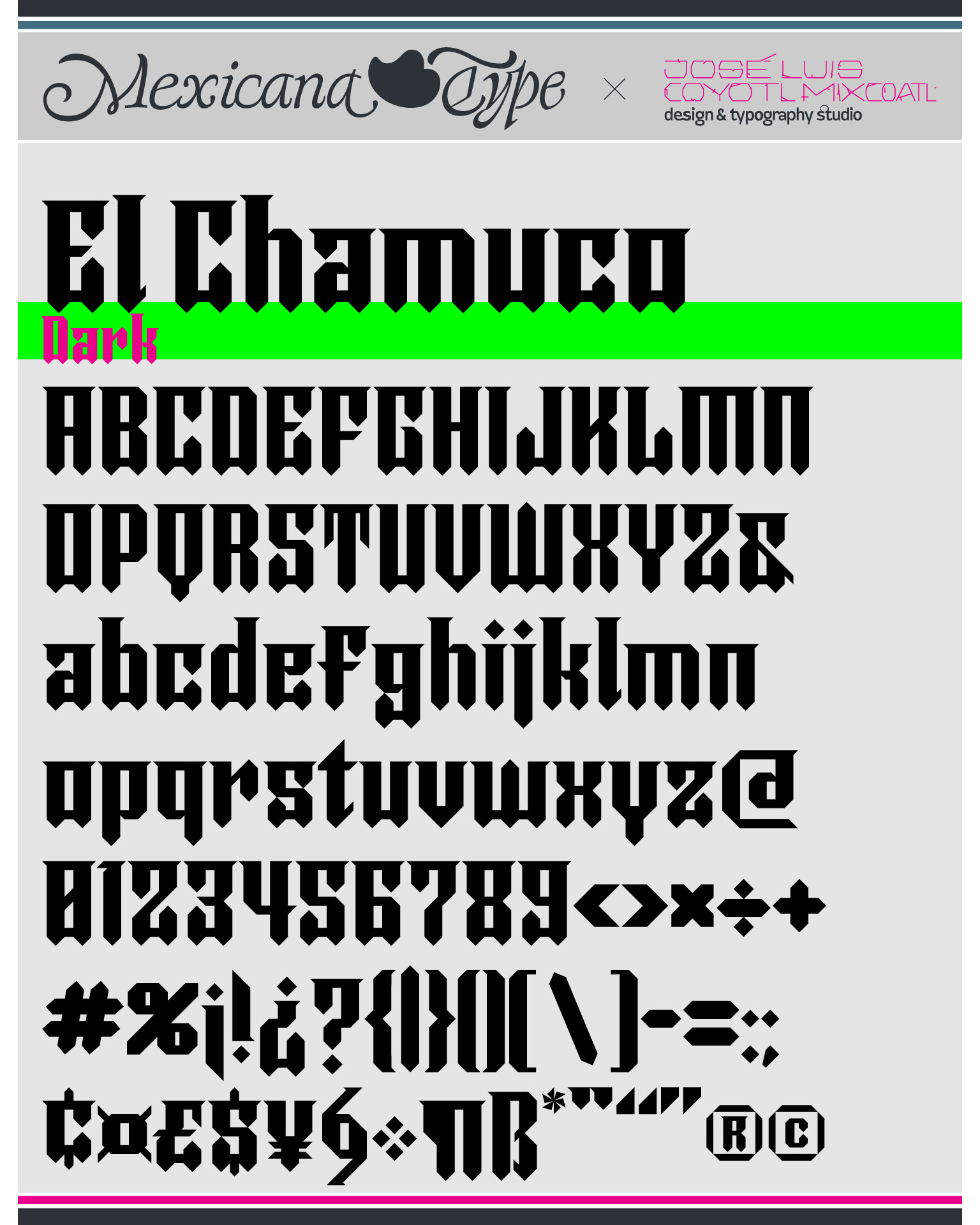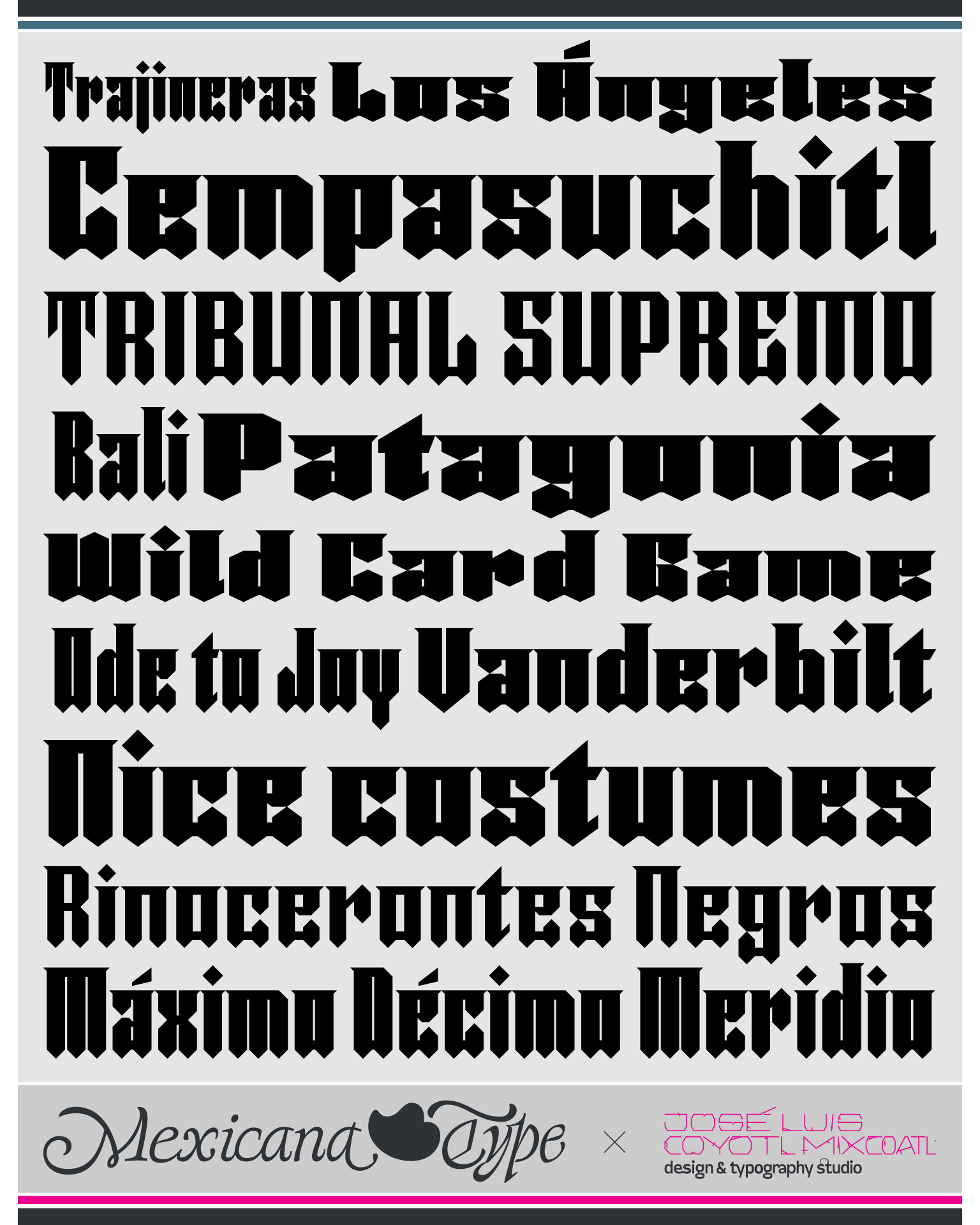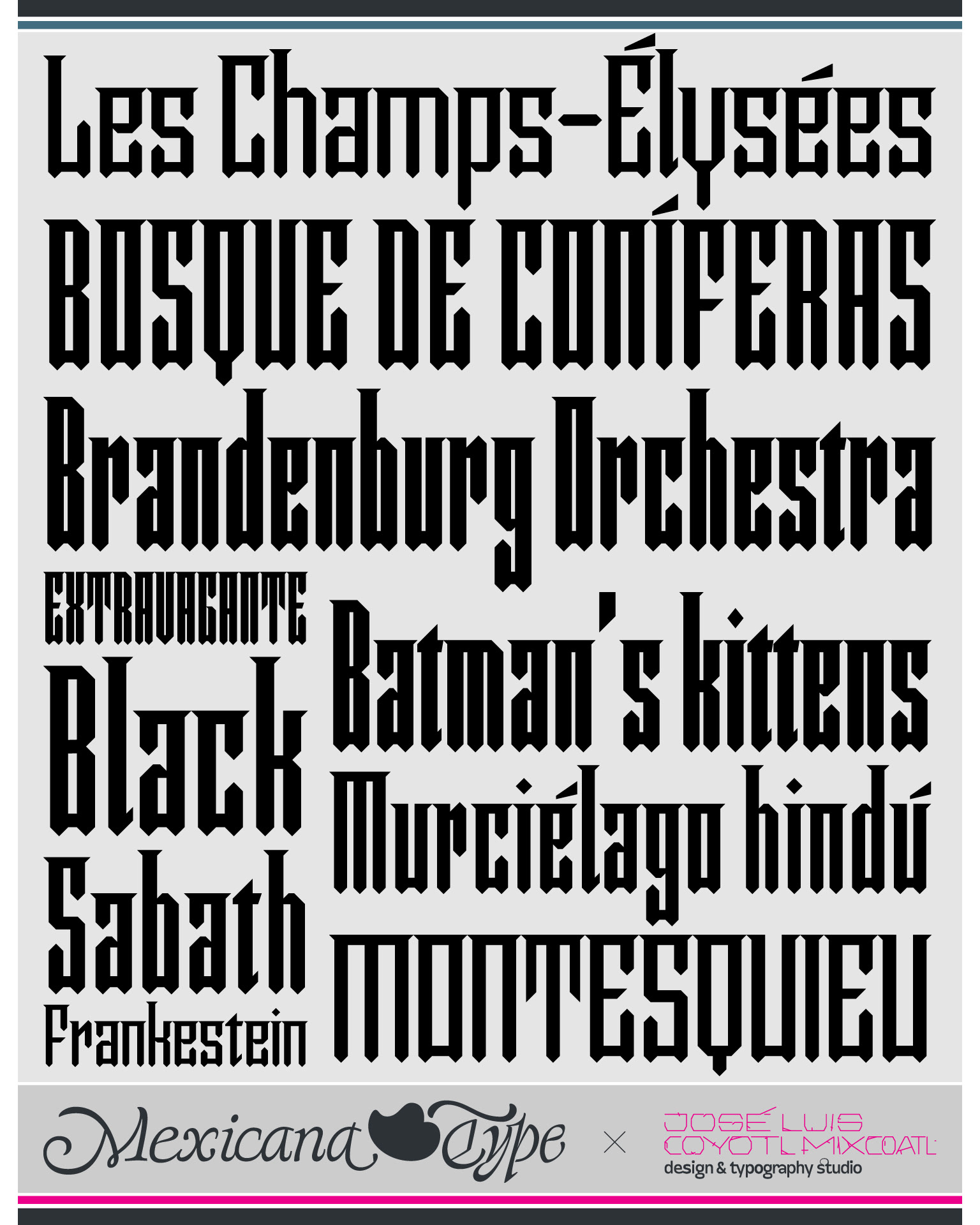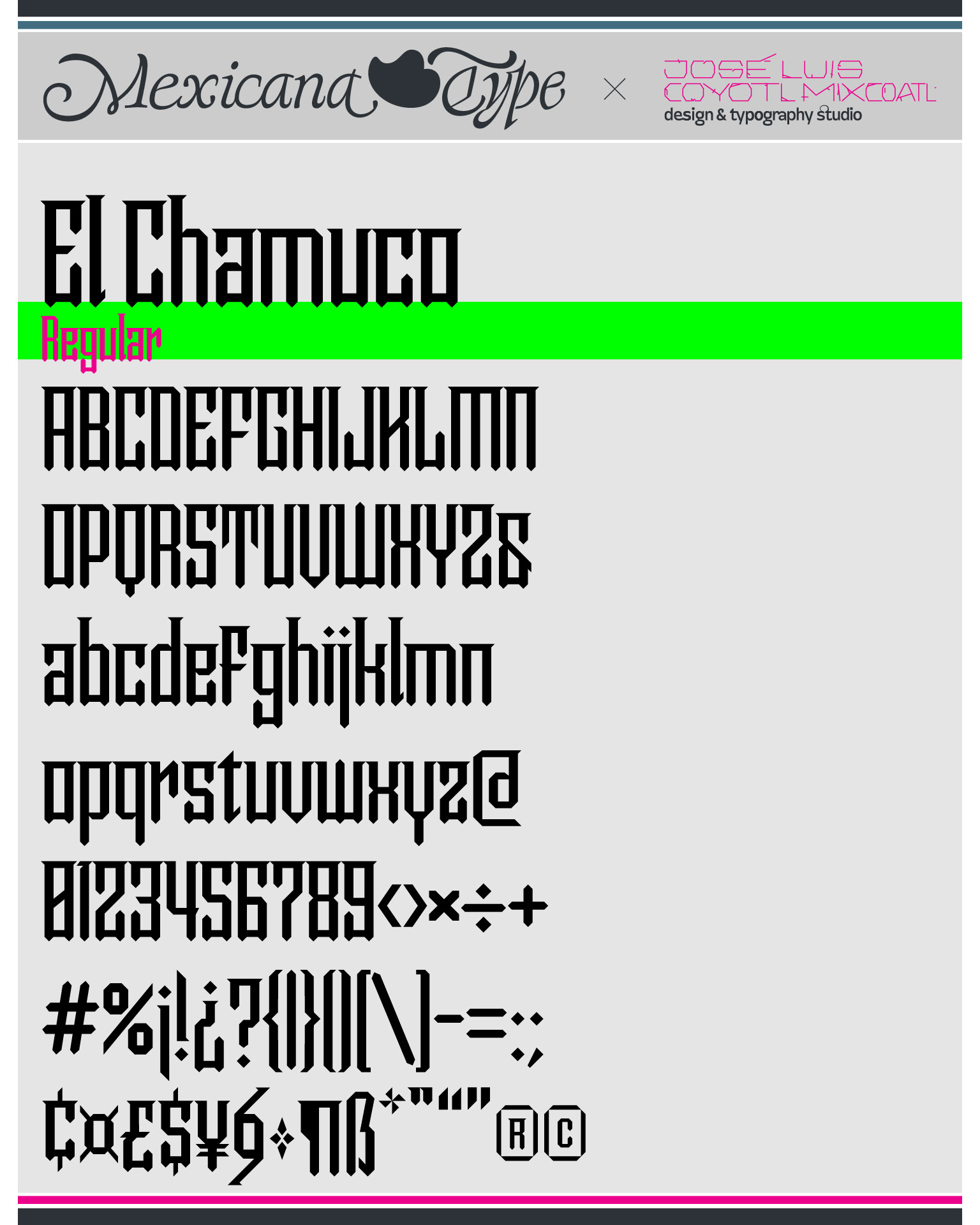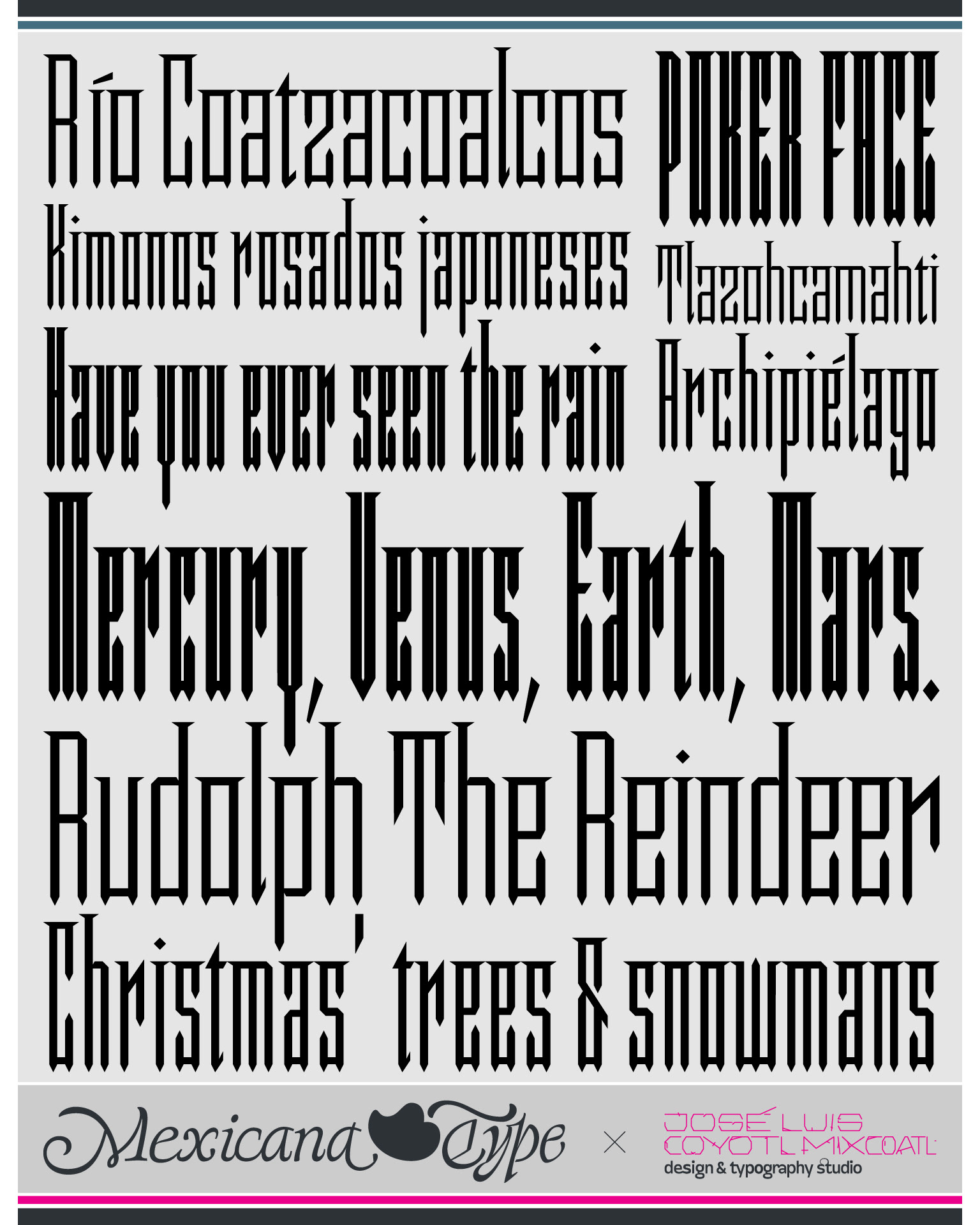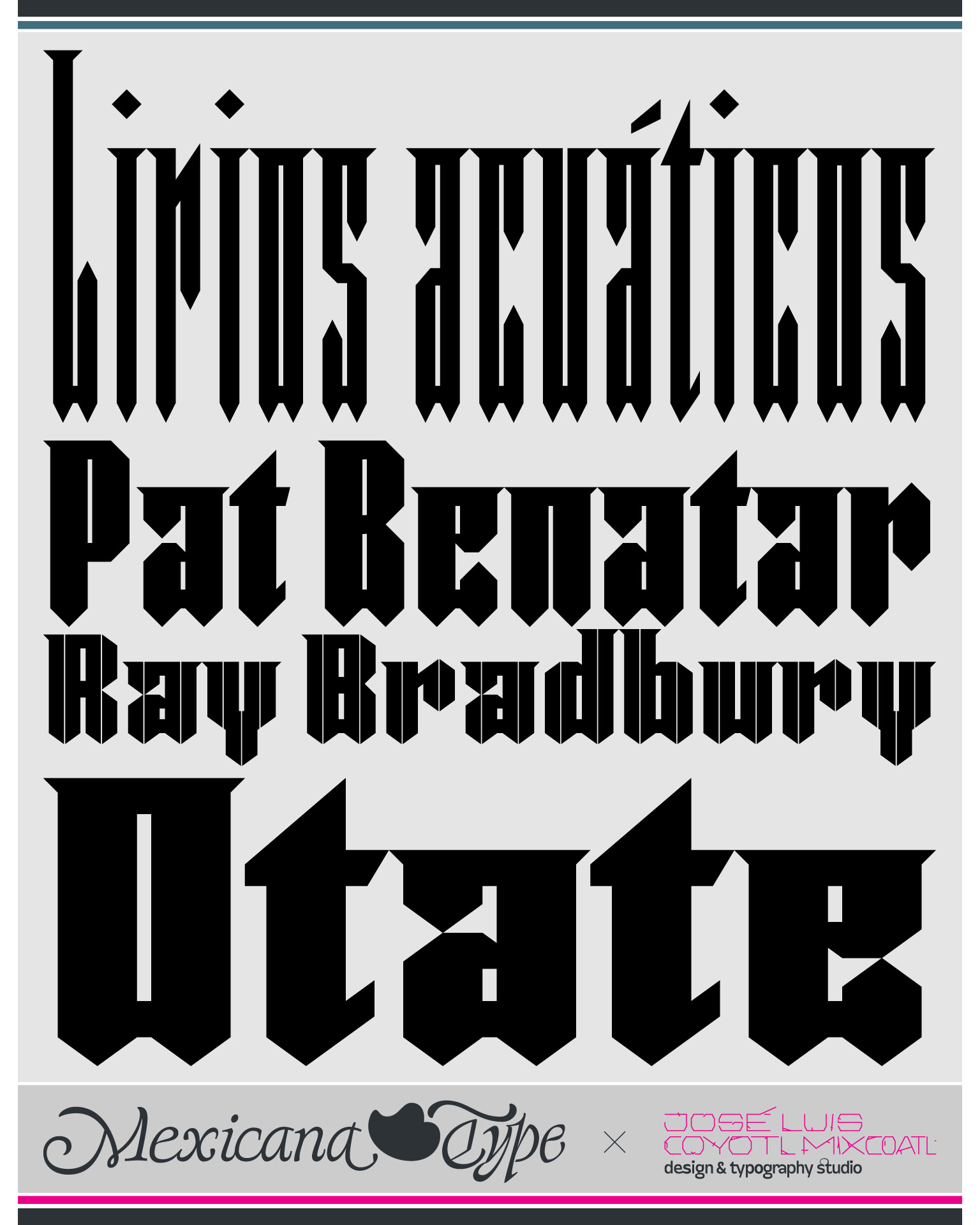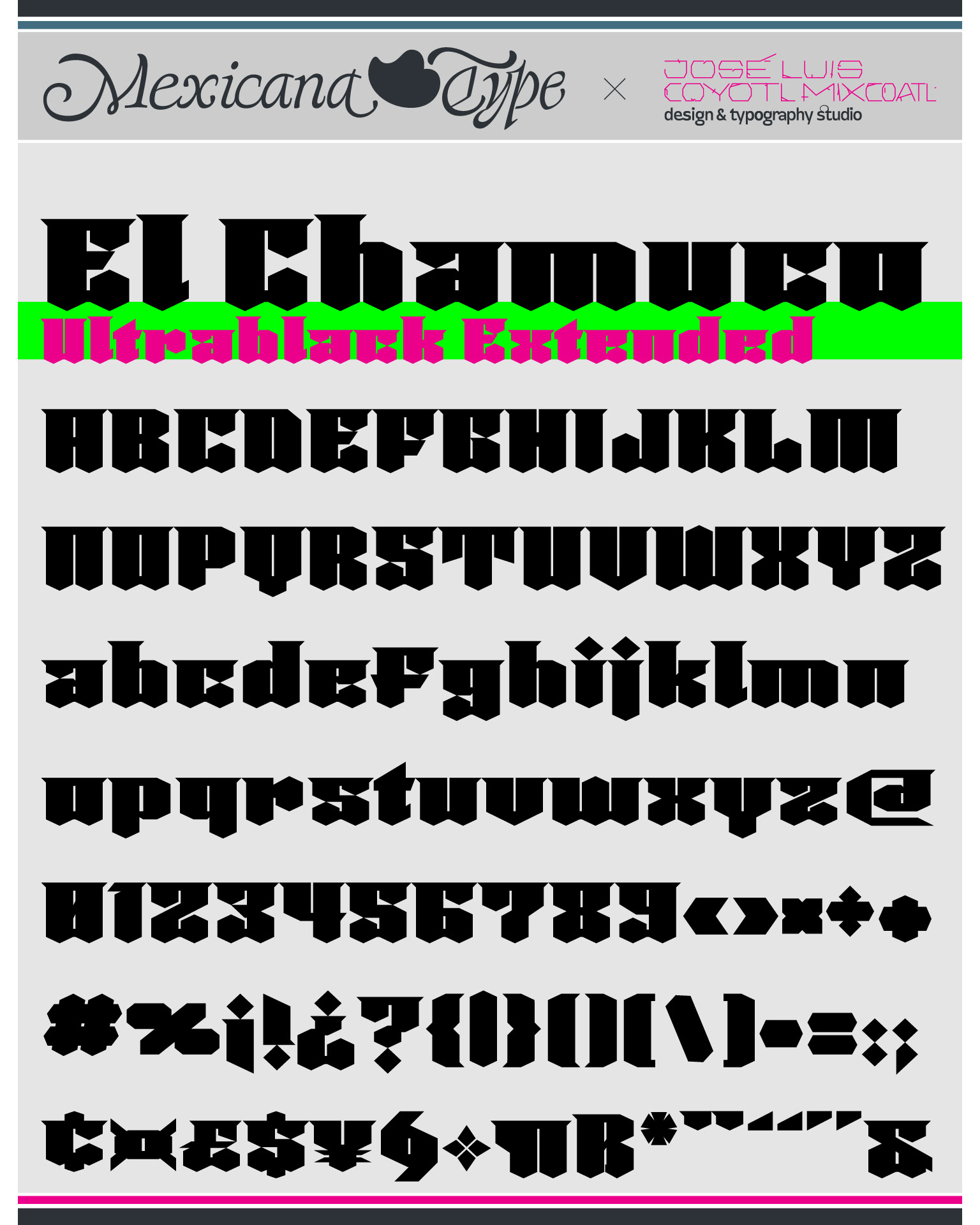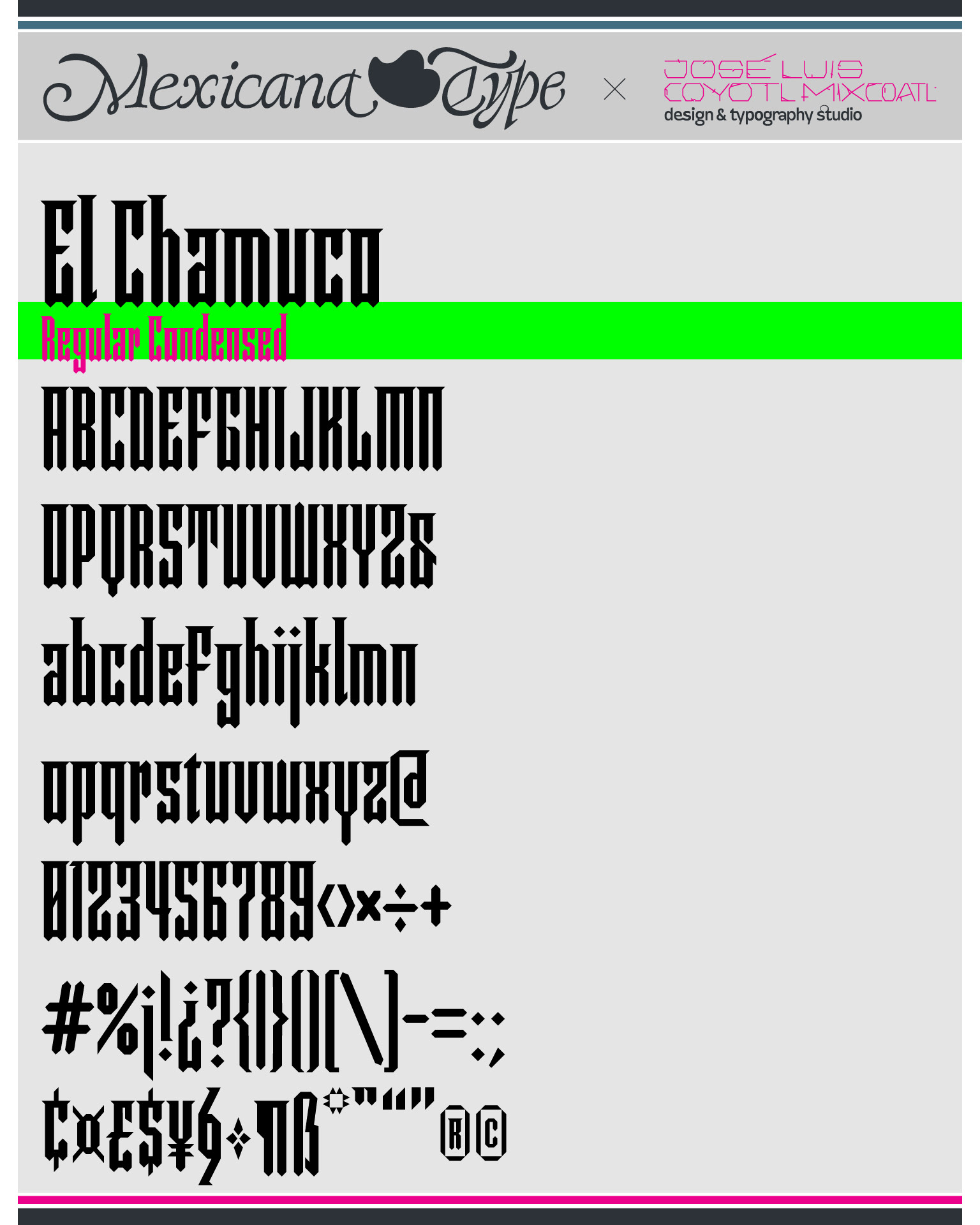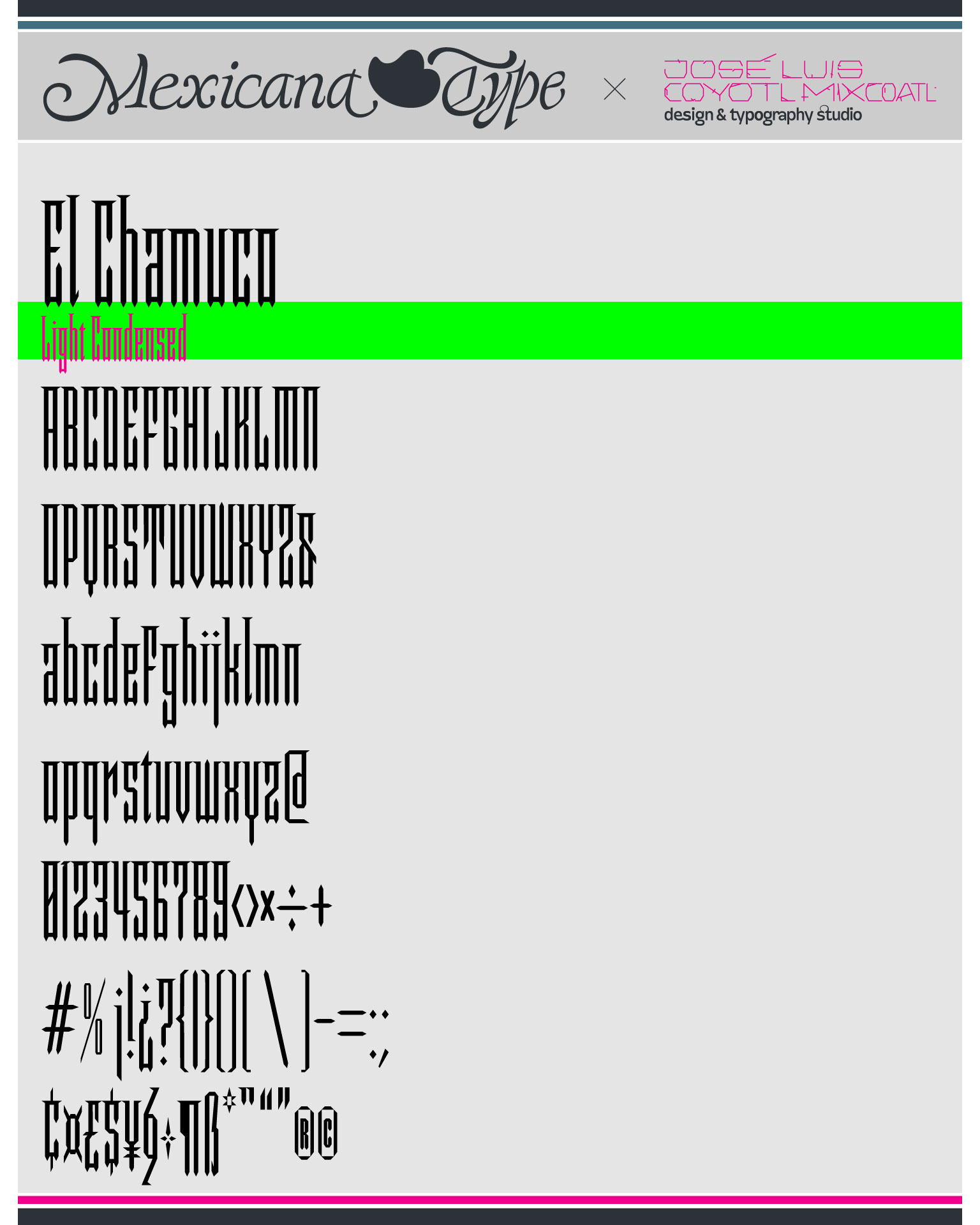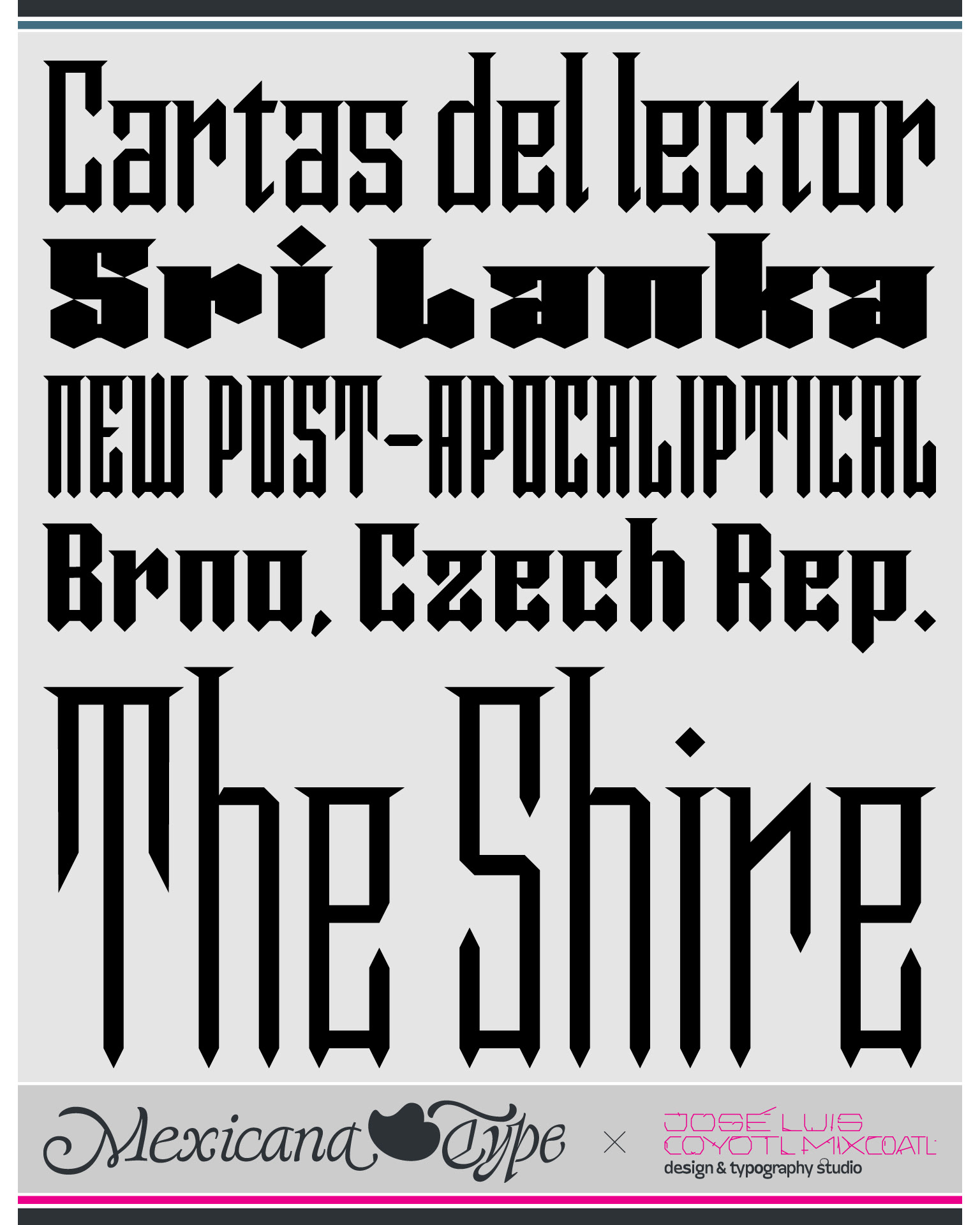
MxT El Chamuco es una tipografía, que es prácticamente la segunda que diseñé, que data de alrededor de 1999 con cuatro pesos, aunque fue ampliada en el 2024 a 13 pesos y variantes con un estilo que remite a algunos trazos, cuerpo y estructura de gótica 'Textur', pero al mismo tiempo con un espíritu modular de letras pintadas a mano y gráfica popular mexicana con un sentido mucho más moderno y contemporáneo. Su diseño permite  un flujo de texto de formas contínuas en sus remates y terminaciones, aludiendo a los cuernos, patas y cola de El Chamuco, personaje muy arraigado en la cultura popular mexicana, y de la que a manera de sátira se recrea en cada una de sus variantes, desde la mas extendida hasta las más condensadas en sus diferentes pesos y, aunque es una tipografía para títulos, también tiene variantes estilísticas aún más display que le dan un enfoque muy singular y con las posibilidades de tener combinaciones muy interesantes en sus bloques de textos, permitiendo eficiencia de espacio en todas sus variantes pero también en la riqueza de sus formas.